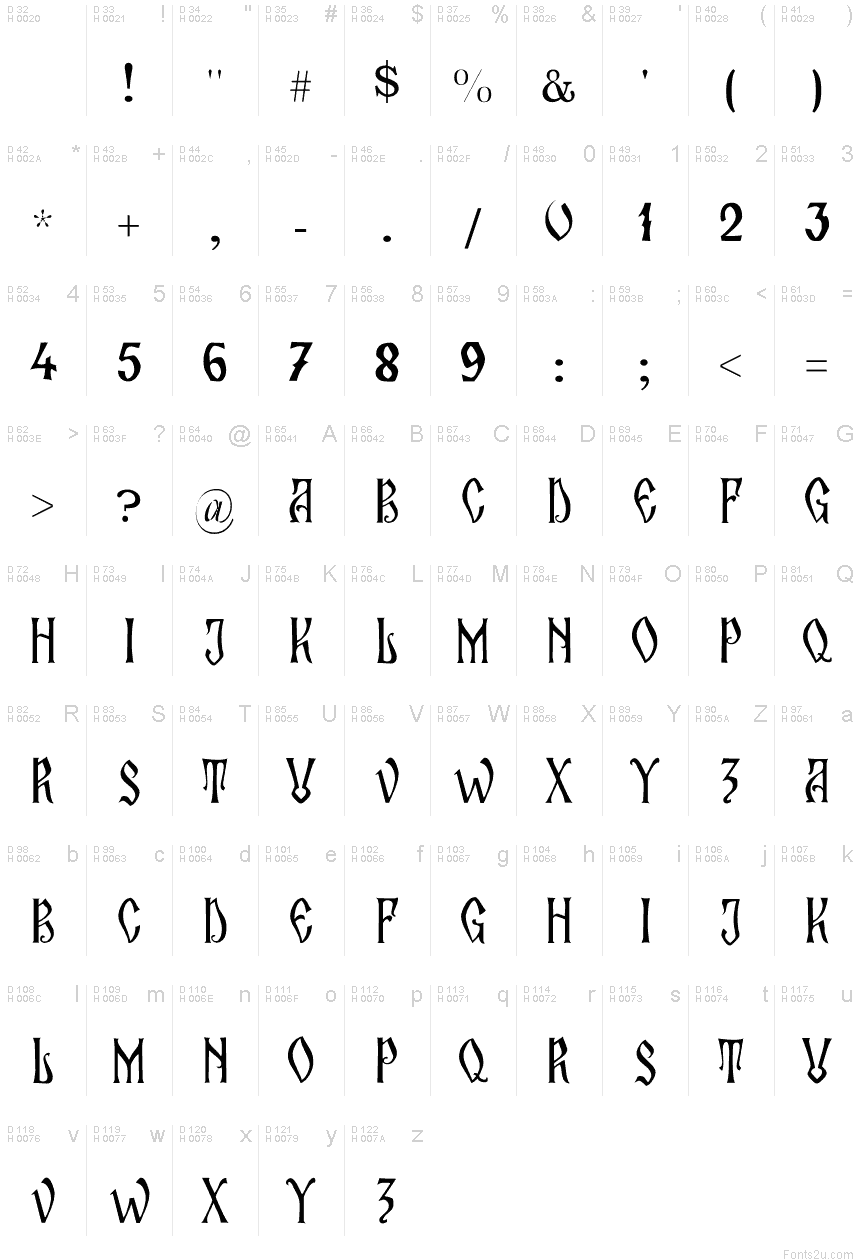
Zamolxis II to darmowy gotycki krój pisma z epoki średniowiecza, o rzeźbionym, ceremonialnym charakterze. Litery łączą ostre kąty blackletter z wysokimi, pełnymi krzywiznami, dzięki czemu słowa sprawiają wrażenie wykutych w kamieniu, a jednocześnie pozostają płynne, z charakterystycznymi ostrymi łączeniami i wyrazistymi, wklęsłymi załamaniami, które powtarzają się w całym zestawie.
Krój sprawdzi się w tytułach na plakatach, okładkach książek, identyfikacjach gier, oprawie festiwali i nagłówkach rozdziałów, wszędzie tam, gdzie darmowy font z taką dawną, poważną nutą wnosi więcej niż zwykłe liternictwo. Użyj go do krótkich nagłówków, plansz tytułowych lub monogramów, gdy chcesz, aby wielkie litery nadały projektowi heraldzki, niemal rytualny ton, bez zbędnego przeładowania.
Mapa znaków czcionki Zamolxis II